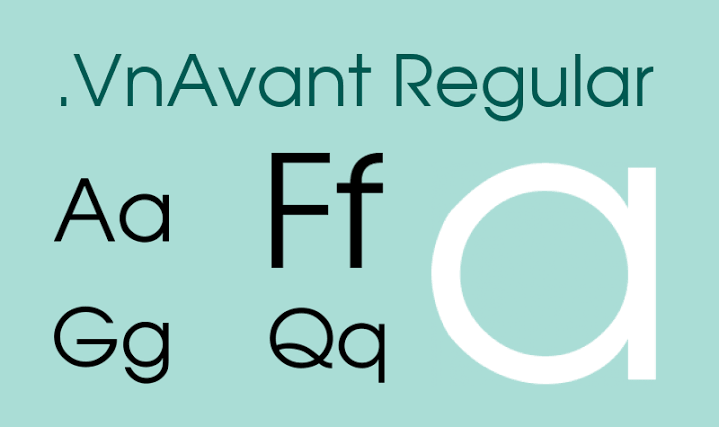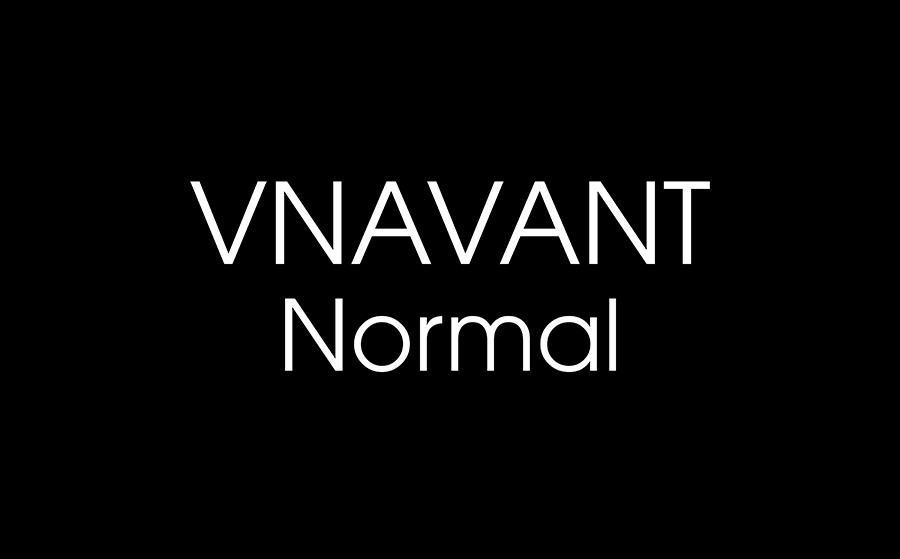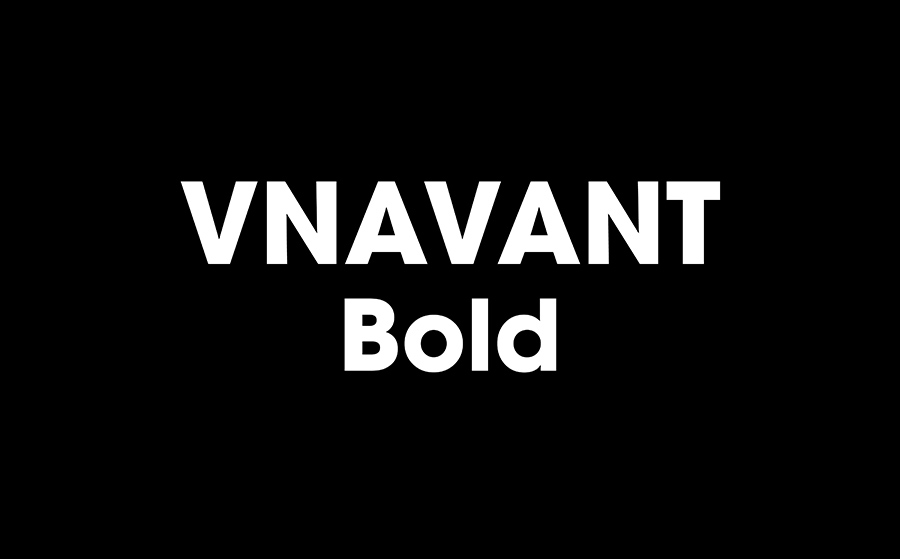
Đặc điểm nổi bật của bộ font chữ VNAvant
VNAvant thuộc hệ thống font ABC (TCVN3), nổi tiếng với sự đơn giản nhưng vô cùng hiệu quả trong việc truyền tải thông tin.
Cấu trúc chữ kiểu đứng dứt khoát và rõ ràng
Đặc trưng lớn nhất khi bạn tải font chữ vnavant kiểu đứng là cấu trúc nét chữ không chân (Sans-serif) với độ dày đồng đều. Các đường nét được thiết kế dựa trên hình khối cơ bản, mang lại cảm giác minh bạch và hiện đại. Chính vì nét chữ “sạch”, không rườm rà nên VNAvant thường được dùng để soạn thảo các tiêu đề báo cáo, bảng biểu hoặc in ấn các thông số kỹ thuật trên bao bì sản phẩm.
Tính ứng dụng trong môi trường giáo dục mầm non
Nhiều giáo viên thường tìm kiếm tải font vnavant mầm non vì đây là bộ font có hình dáng chữ cái gần gũi với bảng chữ cái chuẩn trong sách giáo khoa. Các nét chữ tròn trịa, không chân giúp trẻ em dễ dàng nhận diện mặt chữ, rất phù hợp để làm bảng chữ cái trang trí lớp học, in nhãn tên cho bé hoặc thiết kế các thẻ học trực quan.
| Tên Font | Đặc điểm thị giác | Mục đích sử dụng đề xuất |
| .VnAvant | Kiểu đứng, nét thường | Soạn thảo văn bản, giáo án mầm non, nội dung chi tiết. |
| .VnAvantH | Chữ in hoa toàn bộ | Làm tiêu đề chính, tên công ty hoặc các thông báo quan trọng. |
| .VnAvant Bold | Nét đậm, mạnh mẽ | Dùng in thông số kỹ thuật chính trên bao bì, hộp giấy. |